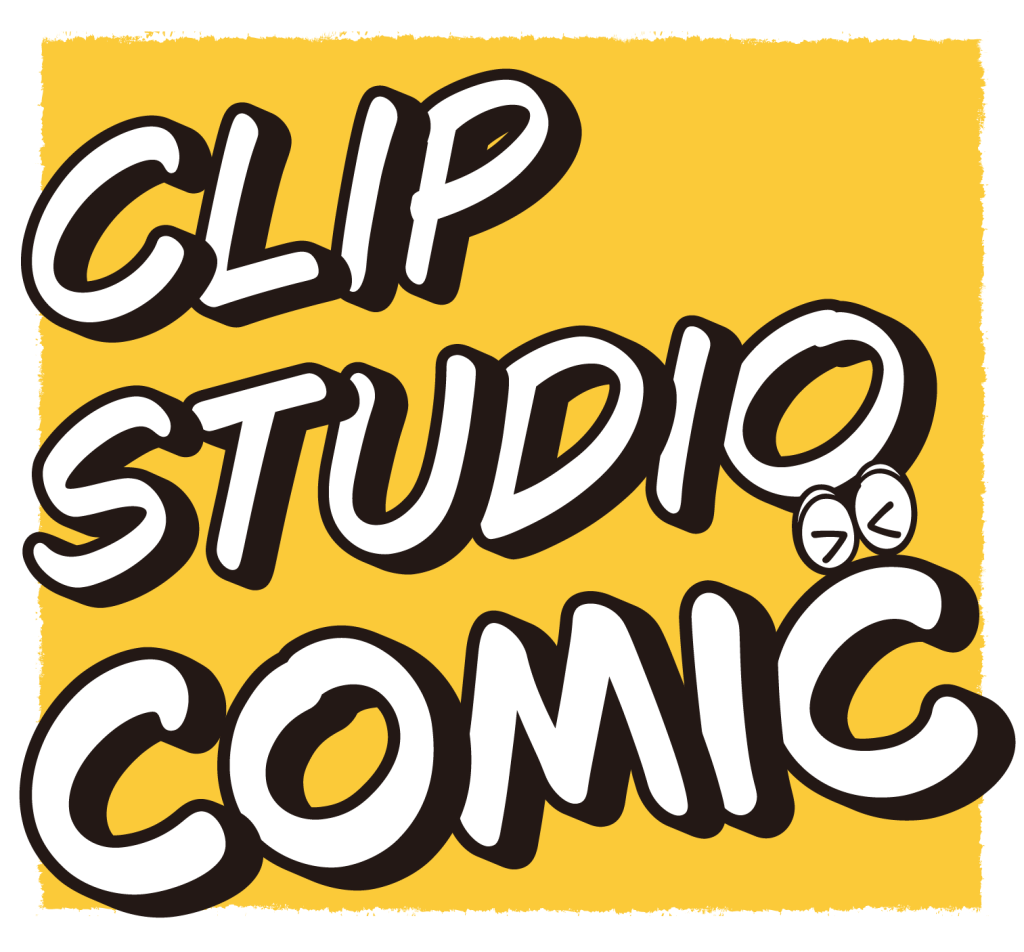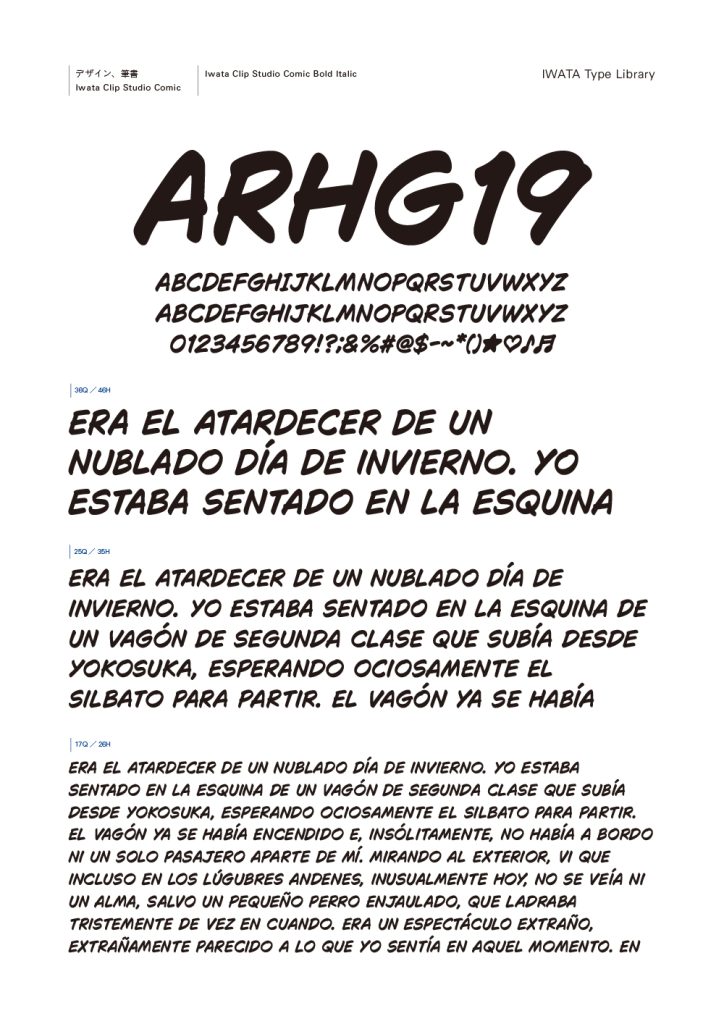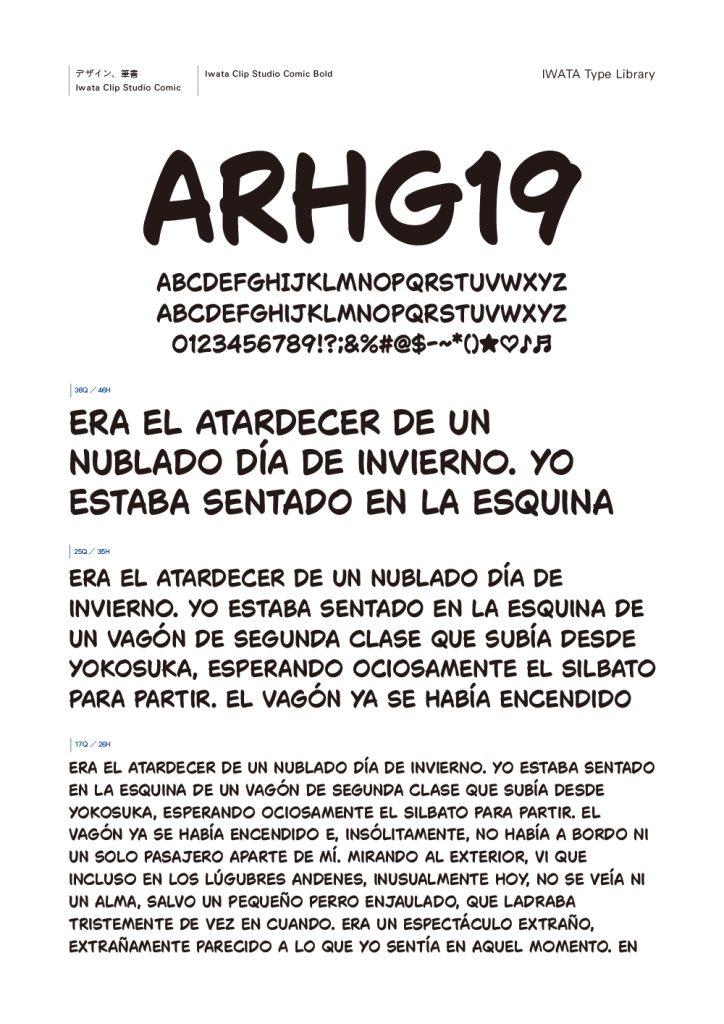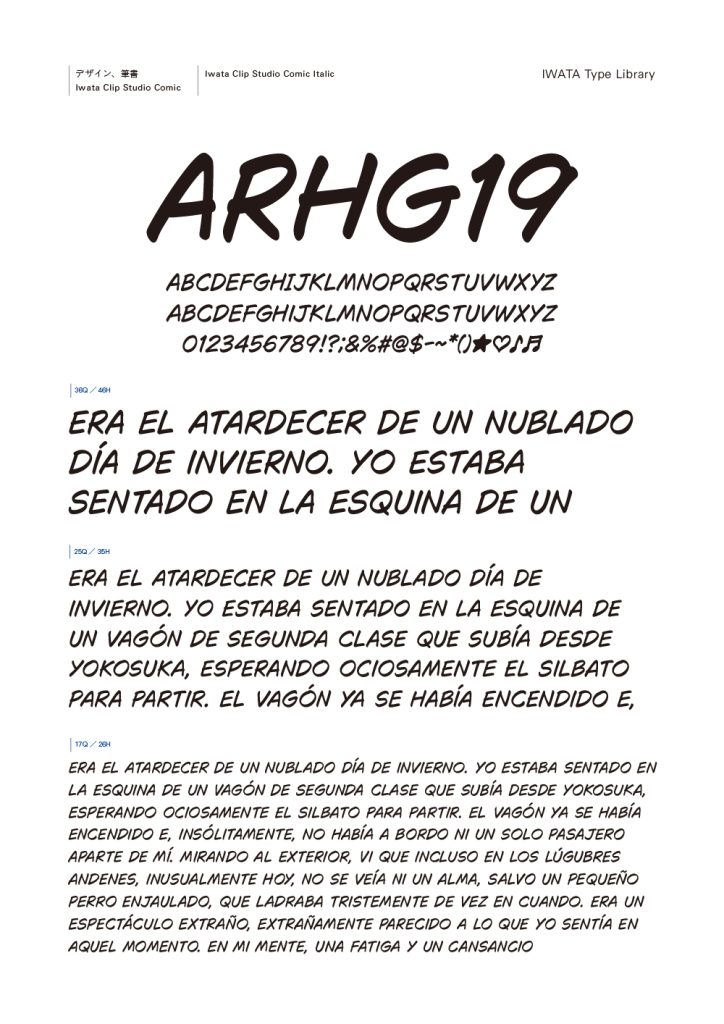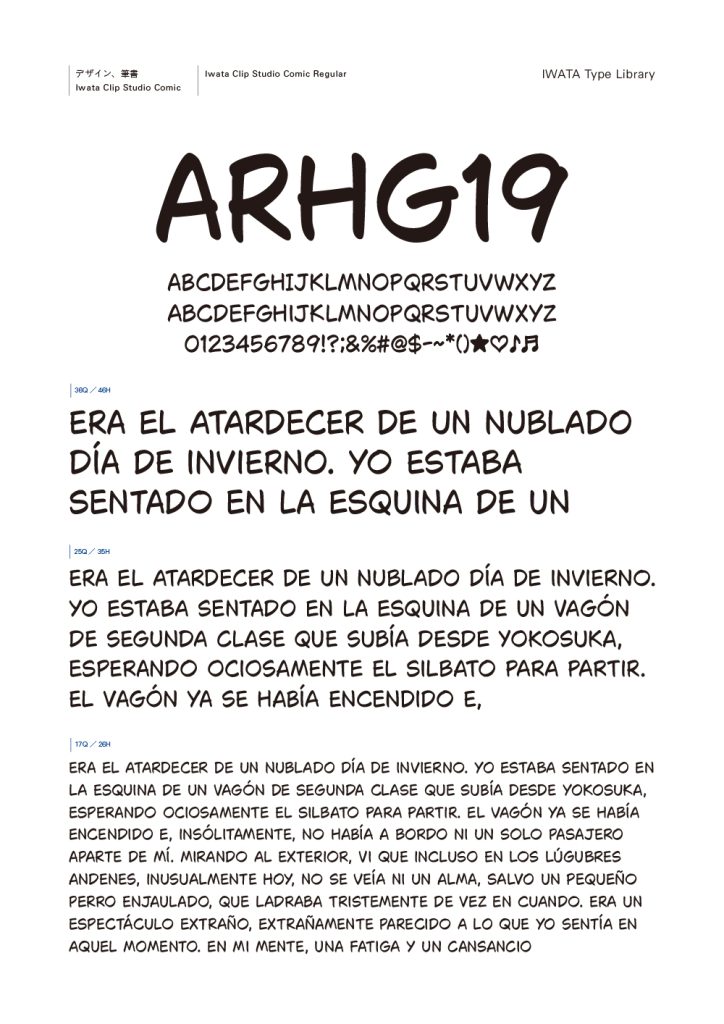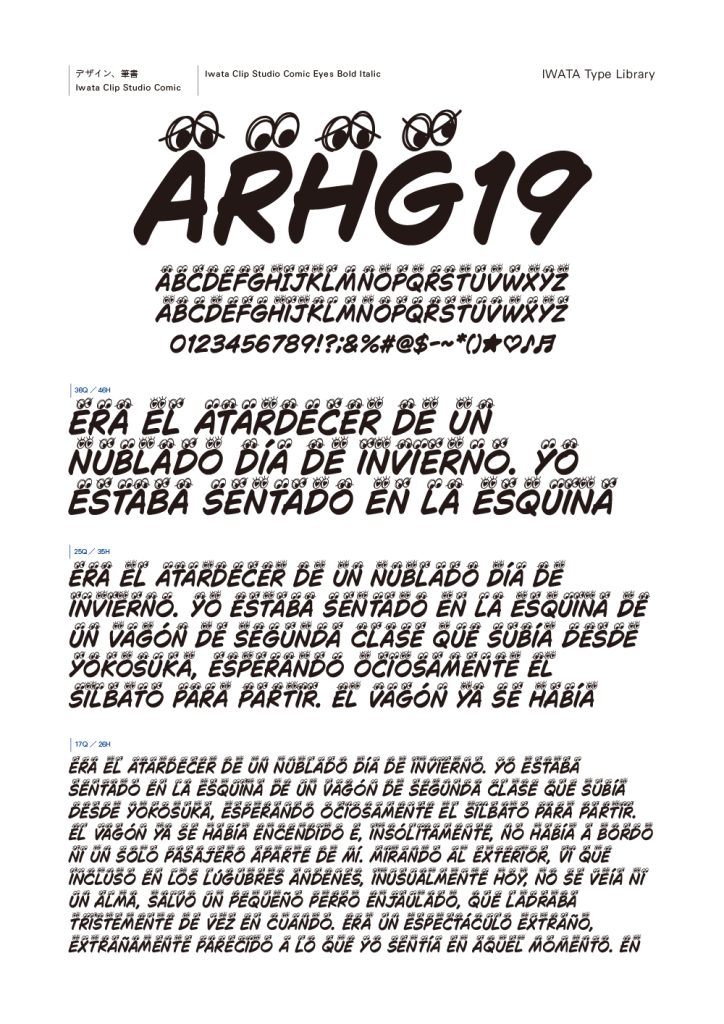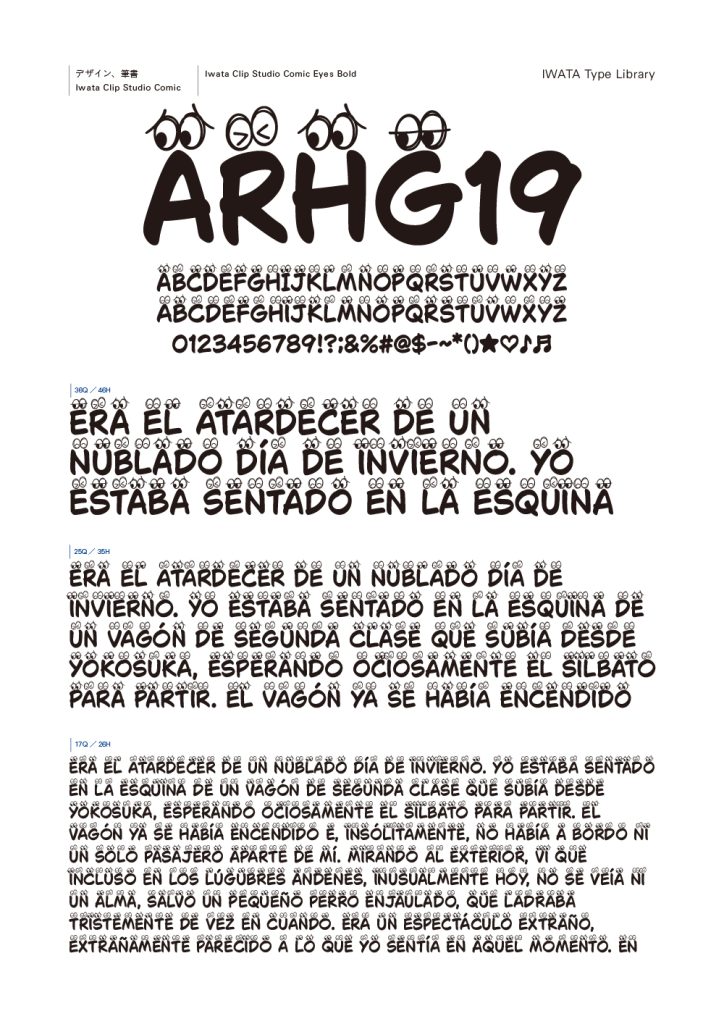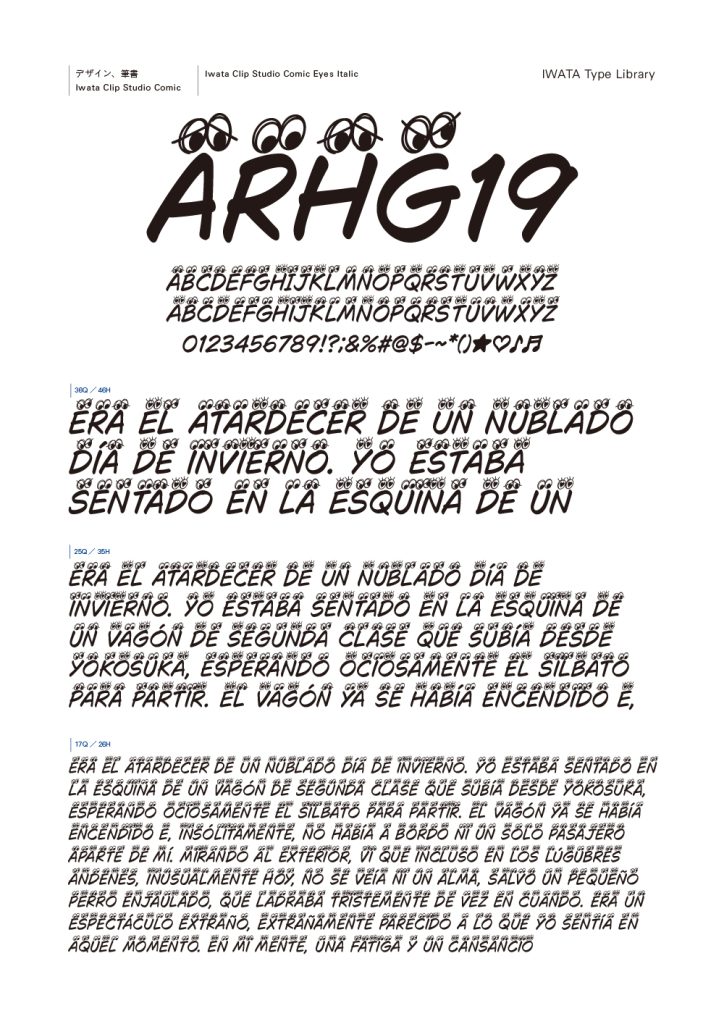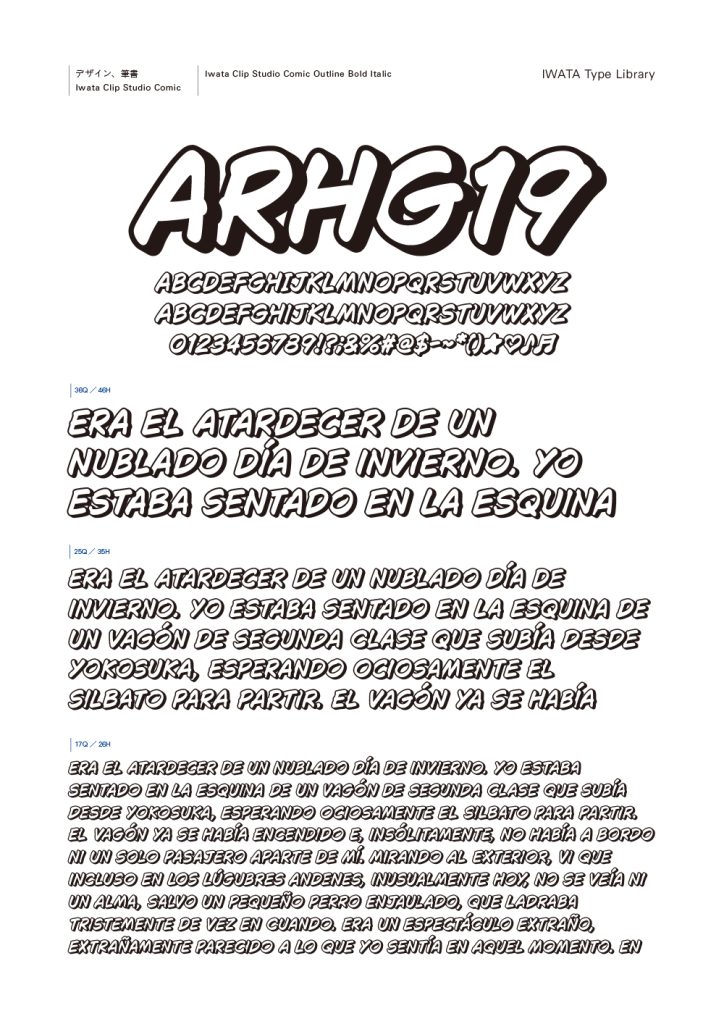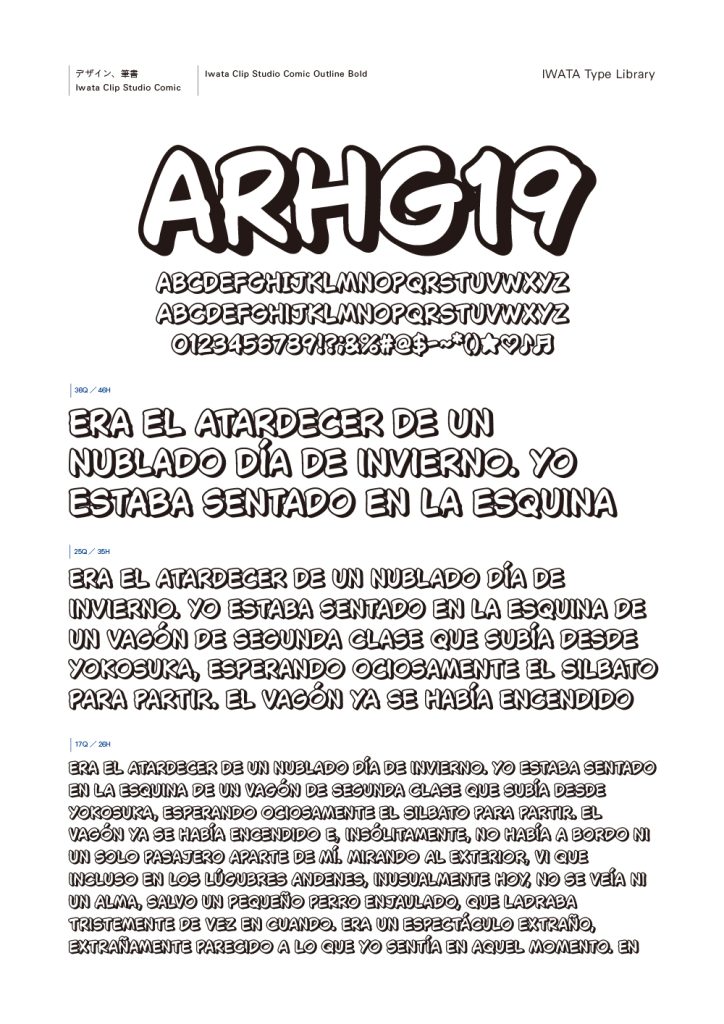
CLIP STUDIO PAINTのブラシツールを使って書かれたラフスケッチを元に開発された、手書き風の欧文書体です。 文字ごとに線の強弱や高さの揺らぎを取り入れ、手書き特有の自然さや親しみやすさを表現。1文字に4つの字形を持たせてランダムに切り替える仕様や、欧米ユーザーの声を反映した文脈に応じて大文字「I」をCrossbar I(上下に横線付き)へ自動変換する機能など、リアルな表現を追求しています。
一般販売に合わせて、「Clip Studio Comic」に絵文字を追加した「Iwata Clip Studio Comic」に加え、縁取りの「Outline」、影のみの「Shadow」、目を加えたユニークな「Eyes」など、多彩なスタイルを収録した「Iwata Clip Studio Comic」ファミリーを用意しました。 Regular、Italic、Bold、Bold Italicにそれぞれ同梱された4書体セットと全てをセットにした16書体セットを用意いたしました。